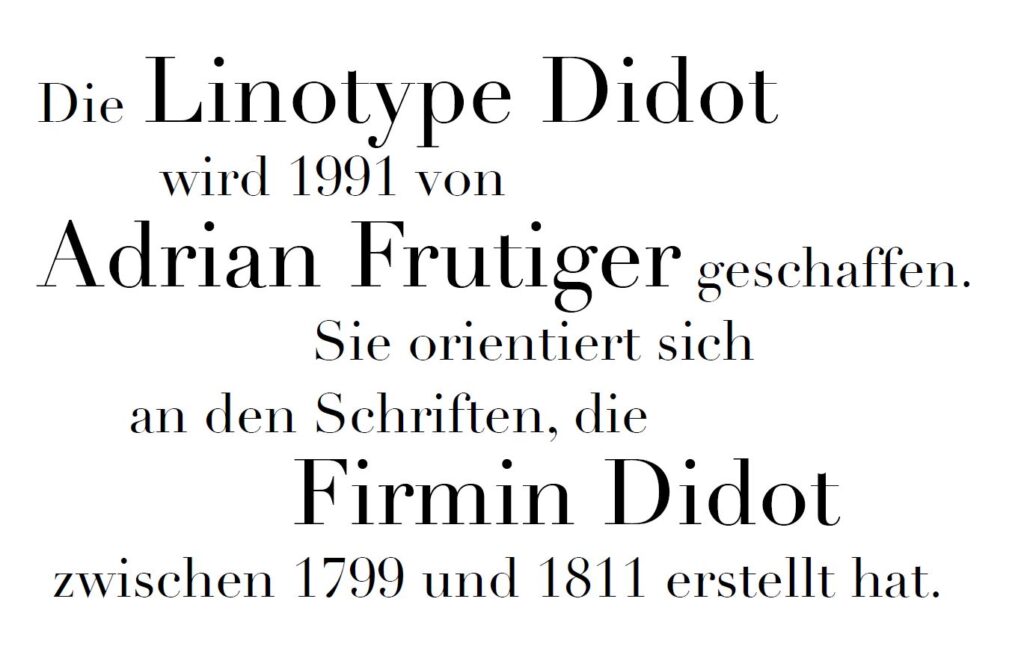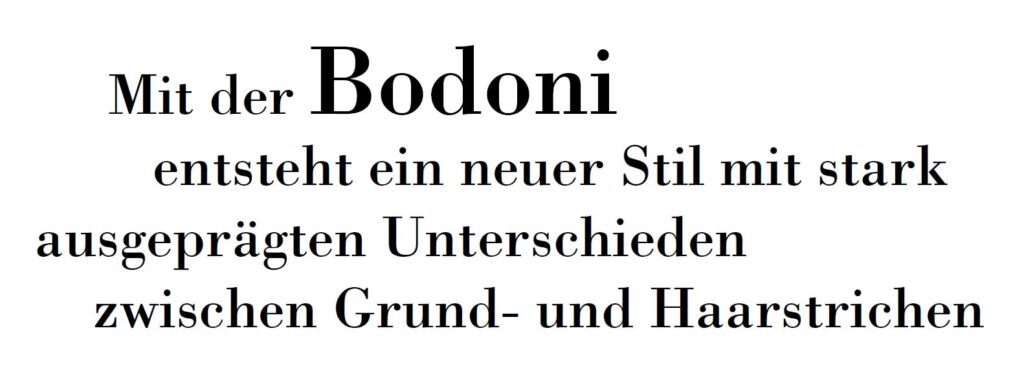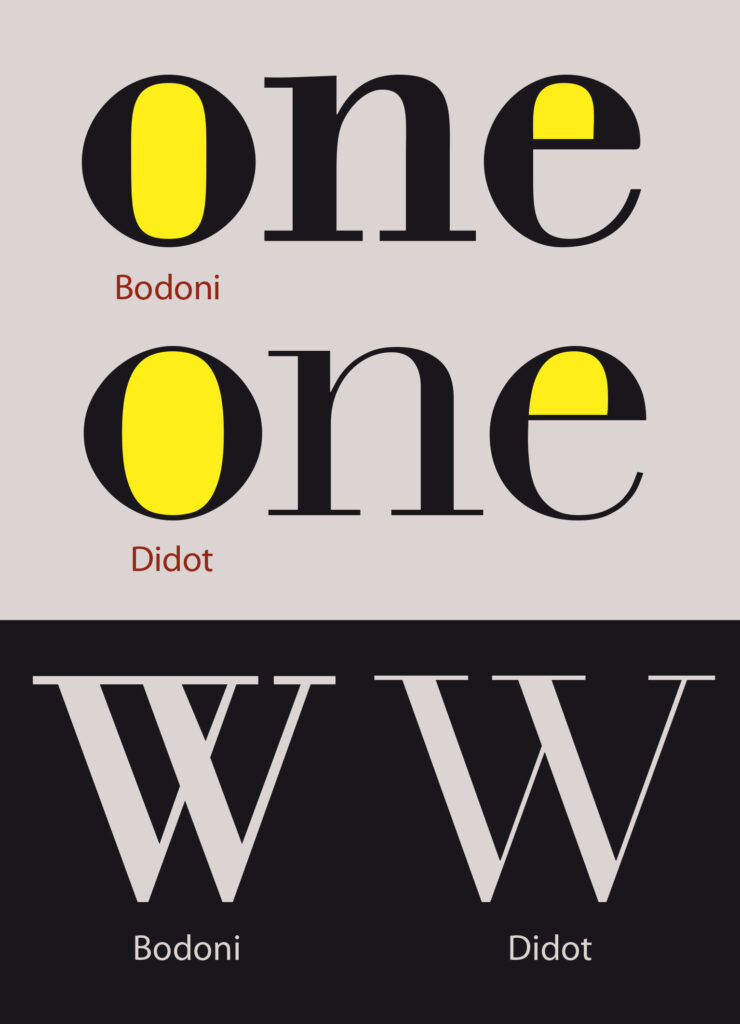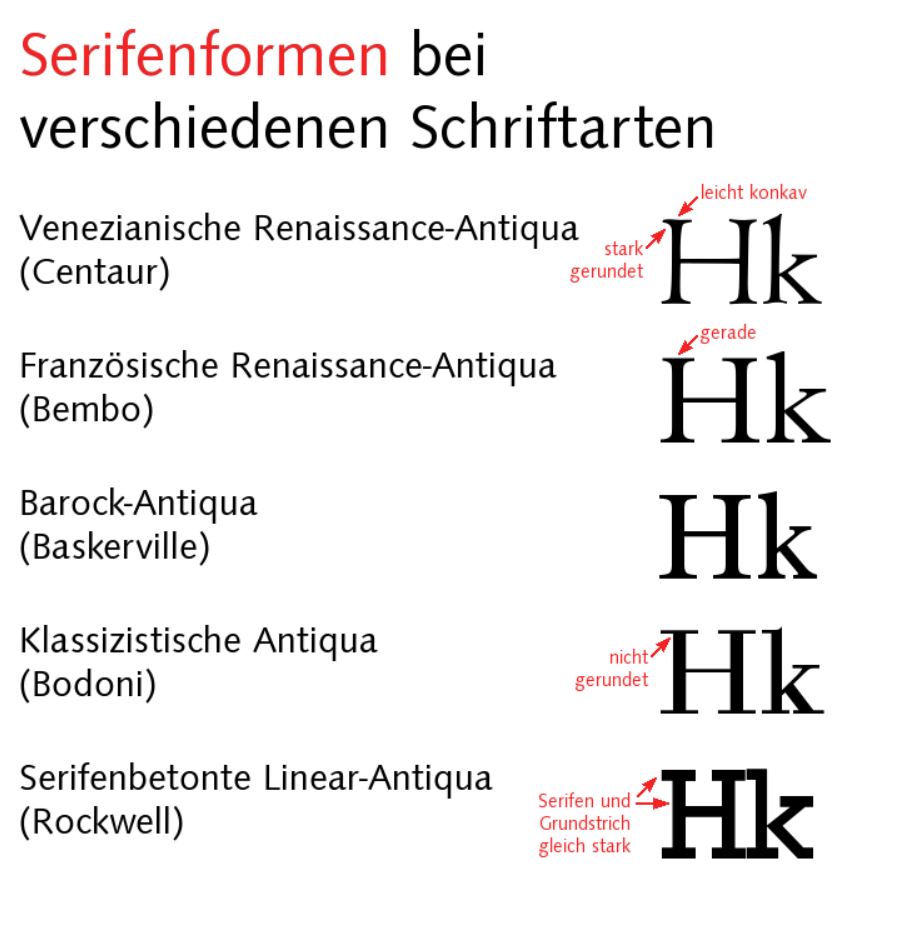
1800 und der Klassizismus
Bereits Mitte des 18. Jahrhunderts begann der Klassizismus, die verspielte Barock- und Rokoko-Kultur mit nüchterner Klarheit abzulösen. Zweckmäßigkeit und Ratio rückten in den Vordergrund, was zu strengen, kontrastreichen Schriftformen führte, die sich an der griechisch-römischen Antike orientierten. Schmuckinitialen verschwanden fast vollständig, Texte wurden klarer und strukturierter gesetzt.
Firmin Didot, Namensgeber des Didot-Punkts, schuf mit der Kaiser-Antiqua zur Krönung Napoleons eine typisch klassizistische Schrift. Sein Maßsystem wurde in vielen Ländern übernommen und stand für Normierung und Ordnung. Kurz darauf entwarf Giambattista Bodoni, der „König der Typografen“, die Bodoni, die zur charakteristischen Vertreterin der Klassizistischen Antiqua wurde. Auch die Walbaum des deutschen Stempelschneiders Justus Erich Walbaum prägte diese Epoche – schlicht, elegant und vielfach überarbeitet. Von ihm stammt zudem eine moderne Form der Fraktur.
Mit der beginnenden Industrialisierung verfeinerten sich die Drucktechniken. Dies führte einerseits zu experimentellen, teils schwer lesbaren Schriften, andererseits auch zu neuen Entwicklungen für Werbung und Gebrauch. 1815 erschien die erste Egyptienne, kurz darauf die erste serifenlose Grotesk. Bereits 1803 hatte Robert Thorne eine Sans Serif vorgestellt, und 1816 veröffentlichte William Caslon eine frühe Grotesk. Den eigentlichen Durchbruch der serifenlosen Schriften markierte später die Akzidenz-Grotesk.